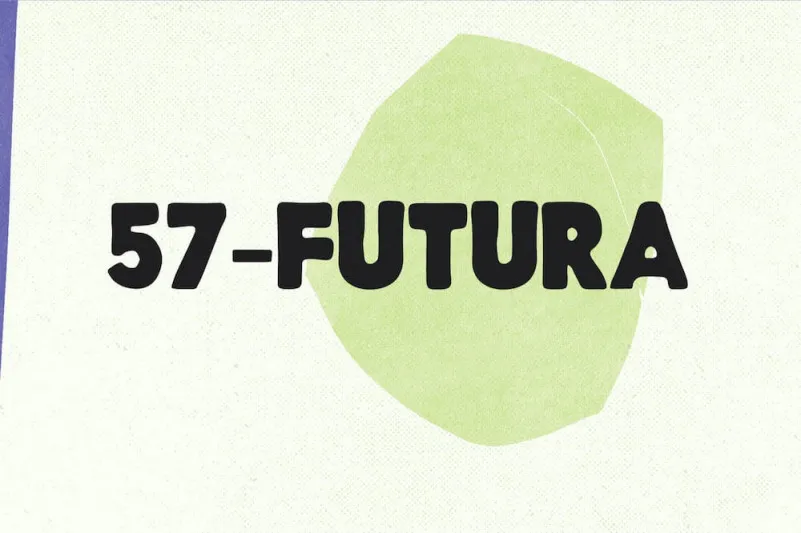
A “57 Futura Font” é uma exuberante fonte para destaque que oferece um toque moderno para qualquer projeto criativo. Seja para logotipos, cartões de visita, embalagens ou até mesmo estampas personalizadas, essa fonte é perfeita para dar vida a sua próxima ideia inovadora. Suavemente futurista e sem deixar de ser versátil, ela adiciona um toque único à sua criação, tornando-a realmente notável em qualquer aplicação visual. Engajante e adaptada para uma variedade de ambientes, essa fonte é certamente uma escolha ideal para quem busca um elemento de destaque inovador e moderno.